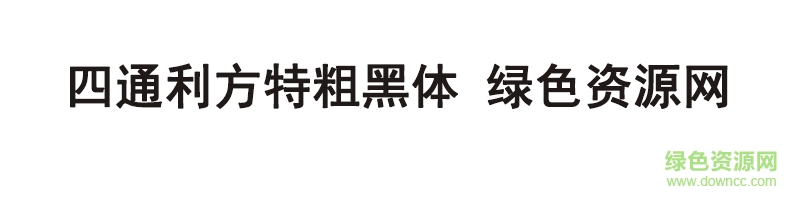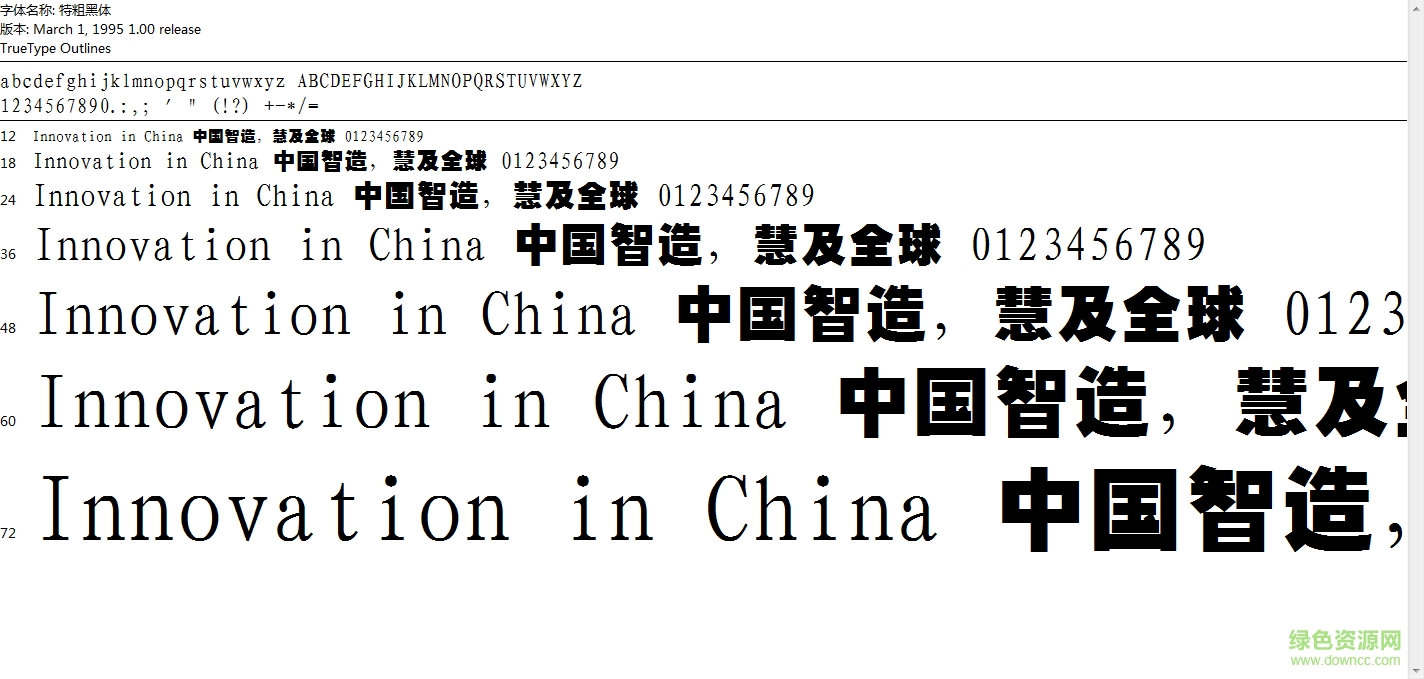
四通利方特粗黑體是專為Windows系統(tǒng)提供的一款字體更換軟件,采用了四通利方字體,字型非常粗,總體干凈利落,可應(yīng)用于廣告設(shè)計(jì)、平面設(shè)計(jì)等場合,歡迎來綠色資源網(wǎng)下載!
四通利方特粗黑體是黑體的一種變體,也是藝術(shù)字的一種。特點(diǎn)是筆劃更粗,盡量將空間充滿。同時為了美觀,對拐彎處的處理較為圓潤。適用于廣告、報刊等的標(biāo)題及海報展板等設(shè)計(jì)場合使用。